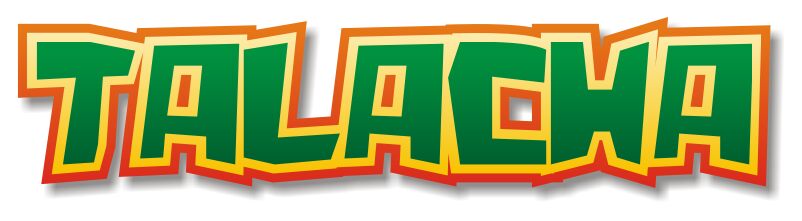
Talacha od Grafito Design to darmowy font typu display o surowym, wycinanym ręcznie charakterze ulicznych plakatów. Litery są masywne i kanciaste, mają ścięte rogi i nieregularny rytm, co nadaje całości szybki, głośny i, w pozytywnym sensie, zadziorny wygląd.
Idealnie pasuje do projektów, które potrzebują surowej energii, a nie wygładzenia: nagłówków na ulotki, plakatów skejtowych czy muzycznych, okładek zinów, plansz tytułowych i odważnych szkiców logo. Jako darmowy font, Talacha najlepiej sprawdza się w krótkich akcydensach, gdzie te poszarpane, improwizowane kształty mogą grać główną rolę, zwłaszcza w nagłówkach czy monogramach, które mają mieć domowy, wklejany charakter.